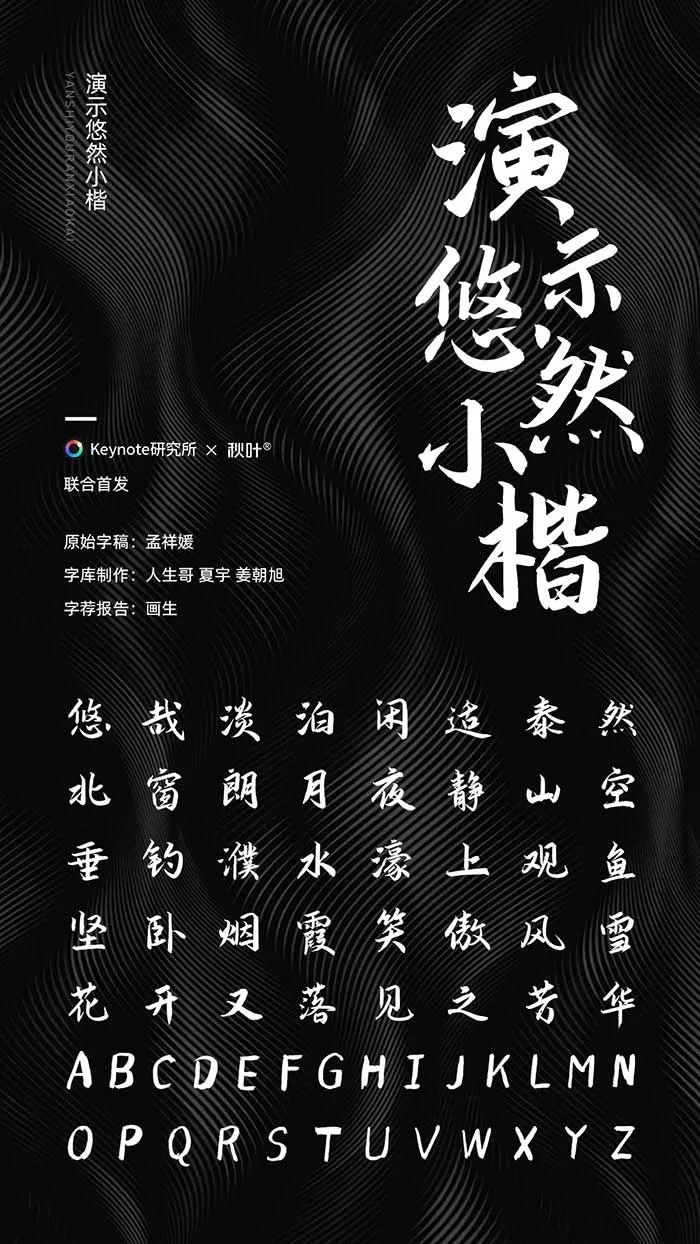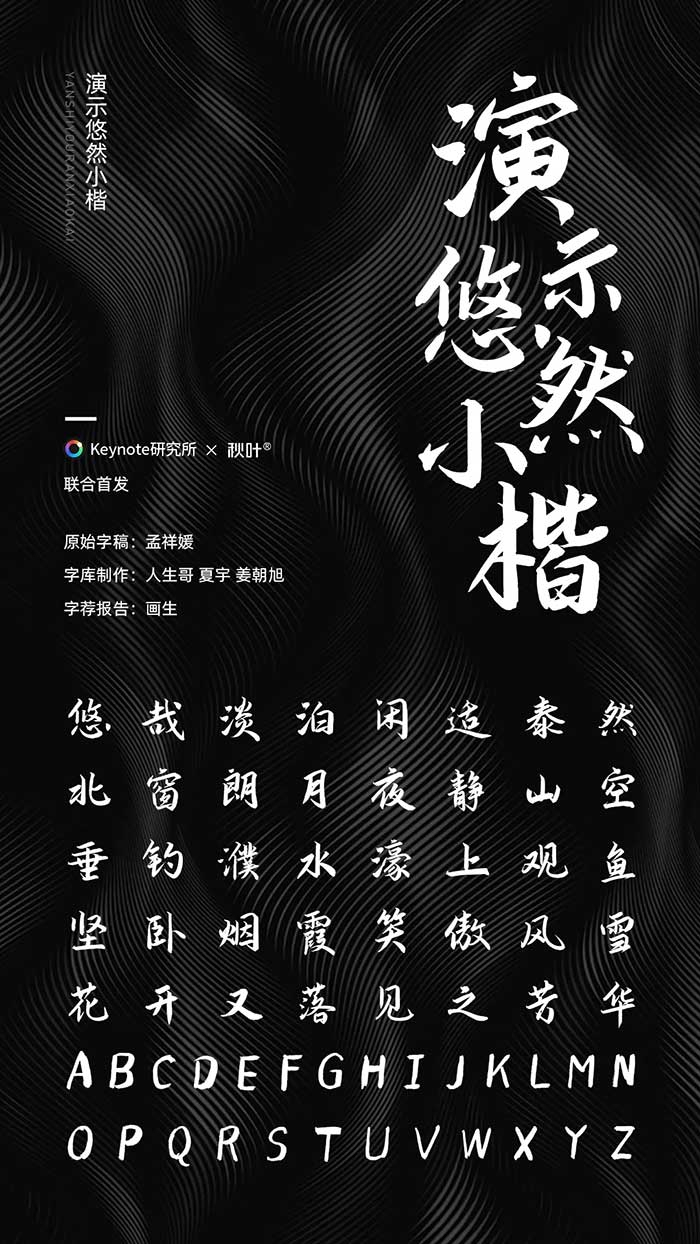
《辭海》有語:形體方正,筆畫平直,可作楷模。說的,便是楷書。始於漢末,因其工整規範、乾淨利落的特點,通行至現代,長盛不衰。楷體中以小楷清秀流麗、潤澤含蓄,可填補系列字的中庸之位,於是便有了這款——演示悠然小楷。
寫出這套字的是一位很漂亮的女孩——孟祥媛,生於1999年,是一位目前還在大學就讀的書法專業的學子,由Keynote研究所和秋葉PPT聯合首發,獻給全社會永久免費使用,包括商用。
初看「演示悠然小楷」,可能並不覺得驚豔,再品,卻會發現透著質樸、率真的氣息。正如尚在象牙塔中的作者本人,那是未經雕琢的拙樸書生氣。
悠然小楷筆畫分明,結構清晰,沒有過度的連筆和飛白,對閱讀識別更為友好;小楷字形較小,天然擁有更大的字間距,即便作為長段文字使用,閱讀上也不會有太大視覺壓力;悠然小楷的筆畫力度分佈均衡,起收有序,沒有太過強烈的對比,自然沉勁而不漂浮;在小楷的基礎上有些行楷的影子,為字體增添了靈動,但又有剋制,形成停而不斷、筆斷意連之態;部分筆畫細節可能並不完美,不夠順滑,但這份未經雕琢,又何嘗不是一種難得的拙樸!